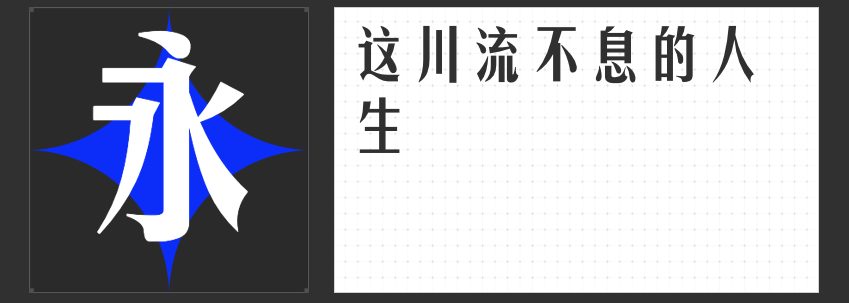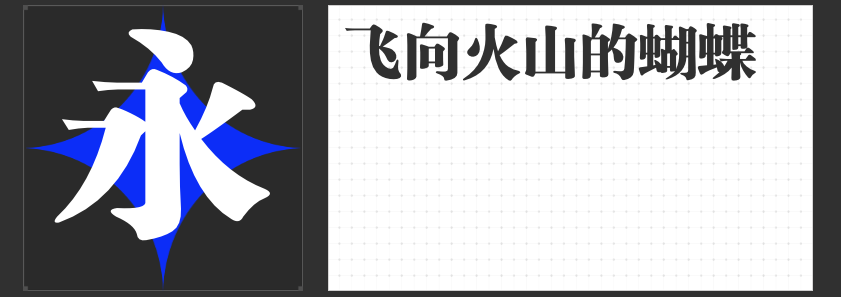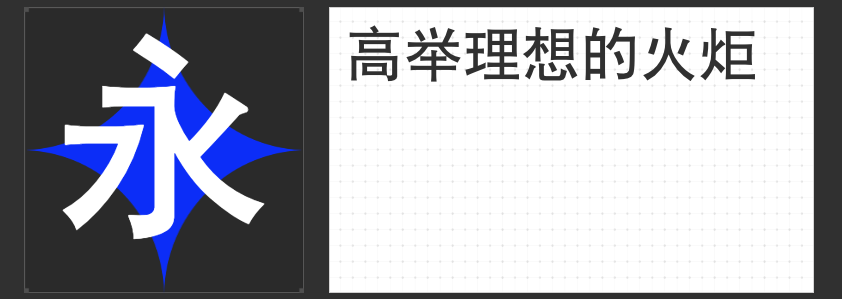
电商详情页字体精选:四款“励字”字体,打造专业与美感并存的购物体验
在电商领域,每一个细节都关乎用户体验与转化率。详情页作为商品展示的重要窗口,其字体选择更是不可忽视的一环。今天,我们精心推荐四款“励字”系列字体,它们各具特色,能够完美匹配不同风格的电商详情页需求,助力商家打造专业与美感并存的购物环境。
1.励字魔方黑简
这款字体以其方正、简洁、无装饰的独特风格脱颖而出,非常适合用作详情页的大标题。它的设计简洁明了,能够迅速抓住顾客眼球,使重点信息一目了然,是提升页面层次感和引导阅读的最佳选择。
2.励字黑体简繁
笔画超粗而有力,字形结构严谨,朴素大方又不失稳重醒目。这款字体特别适用于详情页的小字部分,如商品参数、注意事项等,其清晰简洁的特点能够确保顾客在浏览时轻松阅读,无碍获取信息。
3.励字美黑简
融合了黑体与宋体的精髓,字体匀称、清秀美观,给人以端正又正气的视觉效果。它尤其适合复古风格店铺的详情页设计,能够瞬间营造出一种怀旧而又不失时尚的氛围,让顾客在购物的同时感受到品牌的独特魅力。
4.励字新粗宋简
在保留宋体字基本特点的基础上,打破了传统结体方式,字型扁方而富有新意。这款字体同样适用于详情页的大标题设计,其独特的造型和稳定的视觉效果能够有效提升商品的品质感和档次感,让顾客在第一眼就对商品产生好感。
综上所述,四款字体字体以其多样化的风格和卓越的适用性,成为电商详情页设计的理想选择。无论您的店铺风格如何,总有一款字体能够完美匹配您的需求,助力您打造出更加专业、美观的购物体验。